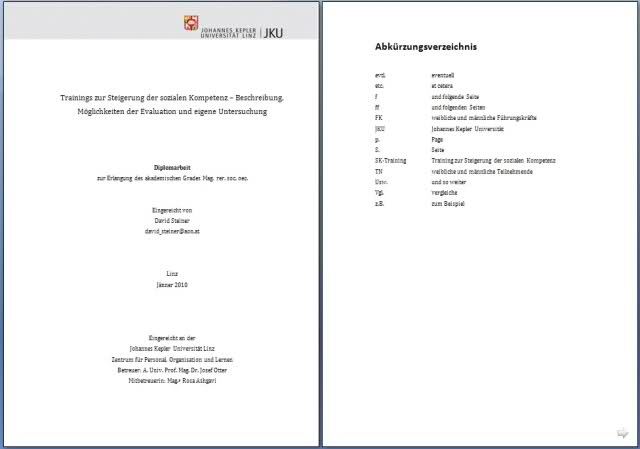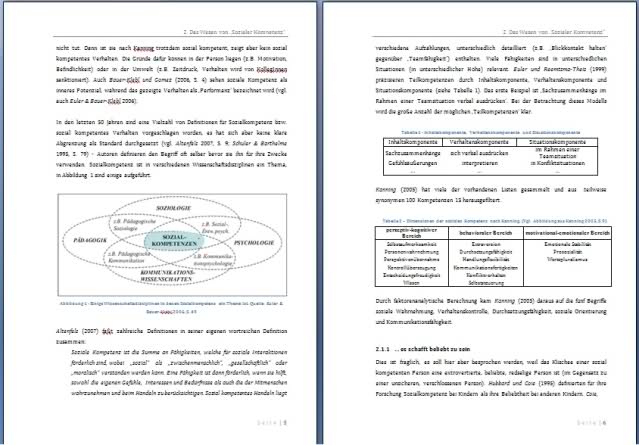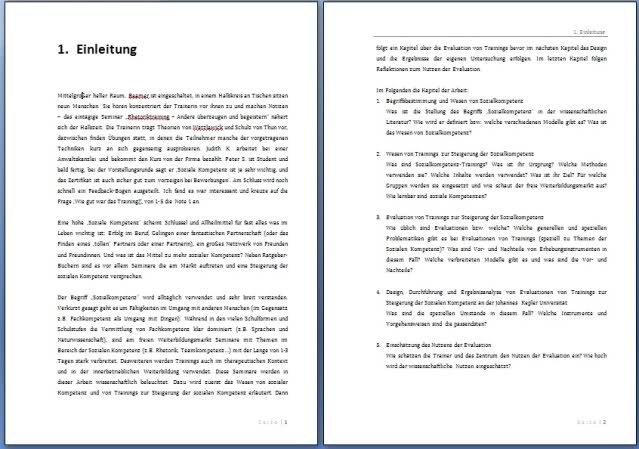
Ich bin Typografie ganz unerfahren, mein Interesse kommt durch das schreiben meiner Diplomarbeit. Die schaut jetzt schon viel besser aus als vorher, yee :)
Ich bin jetzt schon ganz zufrieden. Jetzt wo Ich nicht mehr weiterweiß will Ich euch mein Werk zeigen und freue mich über Kommentare und Meinungen. Was Ihr vielleicht noch machen/probieren würdet.
Die Daten:
Überschriften: Calibri
normaler Text: Cambria 11,5p
Absatz: 1,5 zeilen und 12p 'vor'
Ränder:
oben - 2,5
unten - 3
links - 3,5
rechts - 2
Einseitiger Druck wird es.
ich frage mich, warum Du keine Trennungen zuläßt. Dir großen Löcher in Deinem Text sehen nicht gut aus.
Ich habs leider nicht ganz gecheckt :)
Welche Löcher meinst du genau? Auf Seite 7? (da ist nachher große Grafik auf der nächsten Seite)
Oder dass zwischen Absätzen Leerpausen sind?
aaaah - Silbentrennung! Das meinst du, oder?
Schaut gleich viel blockiger aus :)
Da werden halt alle möglichen Wörter getrennt
Einge-
ständnis
aber gut.
Ich habe Word 2007
Ich habe bei
Silbentrennzone: 0,75cm -> um was geht es da?
Aufeinanderfolgende Trennstrich: 1 -> Was ist dass? Wie viele Trennstriche maximal nacheinander wohl - Ich hab mal 1 - also mindestens nach einer Trennstrich Zeile ist eine normale Zeile wohl. Hm.
Silbentrennzone: 0,75cm -> um was geht es da?
Aufeinanderfolgende Trennstrich: 1 -> Was ist dass?
die ›silbentrennzone‹ ist für den blocksatz uninteressant, da sie sich nur auf den ?attersatz bezieht. der wert bezeichnet den abstand vom rechten rand, den ein wort maximal haben darf, um noch getrennt zu werden, und kontrolliert somit das maß an ?attern.
bei ›aufeinanderfolgende trennstriche‹ solltest du im blocksatz den maximalen wert einstellen. dadurch legst du fest, wie viele zeilen hintereinander mit einem bindestrich enden dürfen. fünf oder mehr davon zu haben, ist natürlich nicht ideal, wobei traditionell drei als maximalwert gilt; ein loch in einer der zeilen wäre aber schlimmer. beim korrekturlesen muss man ohnehin noch mal überprüfen, ob sich trennungen manuell optimieren lassen.
andere anmerkungen:
– das abkürzungsverzeichnis ?nde ich niedlich. wer nicht weiß, was ›evtl.‹ oder ›usw.‹ heißt, wird auch so einiges andere nicht verstehen. ich würde das verzeichnis komplett weglassen und abkürzungen, die tatsächlich nicht unmittelbar verständlich sein könnten, beim ersten vorkommen (wenn sie sehr häu?g sind: im kapitel) ausbuchstabieren.
– anstelle „dieser“ rate ich zu »diesen« anführungszeichen, da letztere innerhalb der x-höhe stehen und sich somit viel müheloser in das zeilenband optisch integrieren.
– die überschriften in calibri müssen nicht fett sein; die größe als auszeichnung genügt. ob die über lesegrößen etwas wurstige calibri die beste wahl ist, sei dahingestellt.
– der bis-strich ist ›–‹ (der sogenannte halbgeviertstrich), nicht ›-‹ (bindestrich). aber achtung: wenn du ›von‹ schreibst, muss das wort ›bis‹ folgen, also ›von x bis y‹ oder ›x–y‹.
– die platzierung eines gedankenstrichs hängt davon ab, welche funktion er erfüllt: umschließt er, wie klammern, einen einschub, stehen die gedankenstriche in derselben zeile wie das erste bzw. letzte wort dieses einschubs. ein einzelner gedankenstrich, der einen bruch im satz ankündigt, steht hingegen besser nicht am anfang einer zeile. man soll am ende der vorangehenden zeile schon sehen können: da kommt jetzt was anderes. erreichen kannst du korrekten umbruch mithilfe von geschützten leerzeichen.
– geschützte leerzeichen brauchst du auch zwischen ›S.‹ und einer seitenzahl – dazwischen darf kein zeilenumbruch! – sowie zwischen den bestandteilen von abkürzungen (etwa ›z. B.‹). elegant wäre in letzterem fall ein halbes leerzeichen, nur da das in ›word‹ eher schwer zu erzeugen ist, ?nde ich das korrekte, aber weniger hübsche ganze leerzeichen akzeptabel.
– das (übrigens grässlich gesperrte) graue ›seite‹ vor der seitenzahl am fuß würde ich weglassen. oder bestehen zweifel, um welche angabe es sich dort handelt?
es gibt sicher noch mehr zu kritisieren und empfehlen, aber ich belasse es vorerst dabei.
ps: ›mag. rer. soc. oec.‹ – hach, manchmal beneide ich euch österreicher doch ein wenig.
Hast du eine Ad-hoc Idee statt der calibri für Überschriften?
Jetzt sind noch ein paar Fragen aufgekommen, vielleicht kann mir da wer helfen:
Ich empfehle Dir, mal Abstände zwischen 14 und 15 Pt auszuprobieren. Als Absatzabstand würde ich 2/3 des Zeilenabstands verwenden, das wären also bei einem Zeilenabstand von 14,5 Pt dann 9,67 Pt. :)
Absatz-abstand - heißt dass die Einstellung bei Absatz: 'Nach:'? ('vor:' bleibt eh bei 0?)